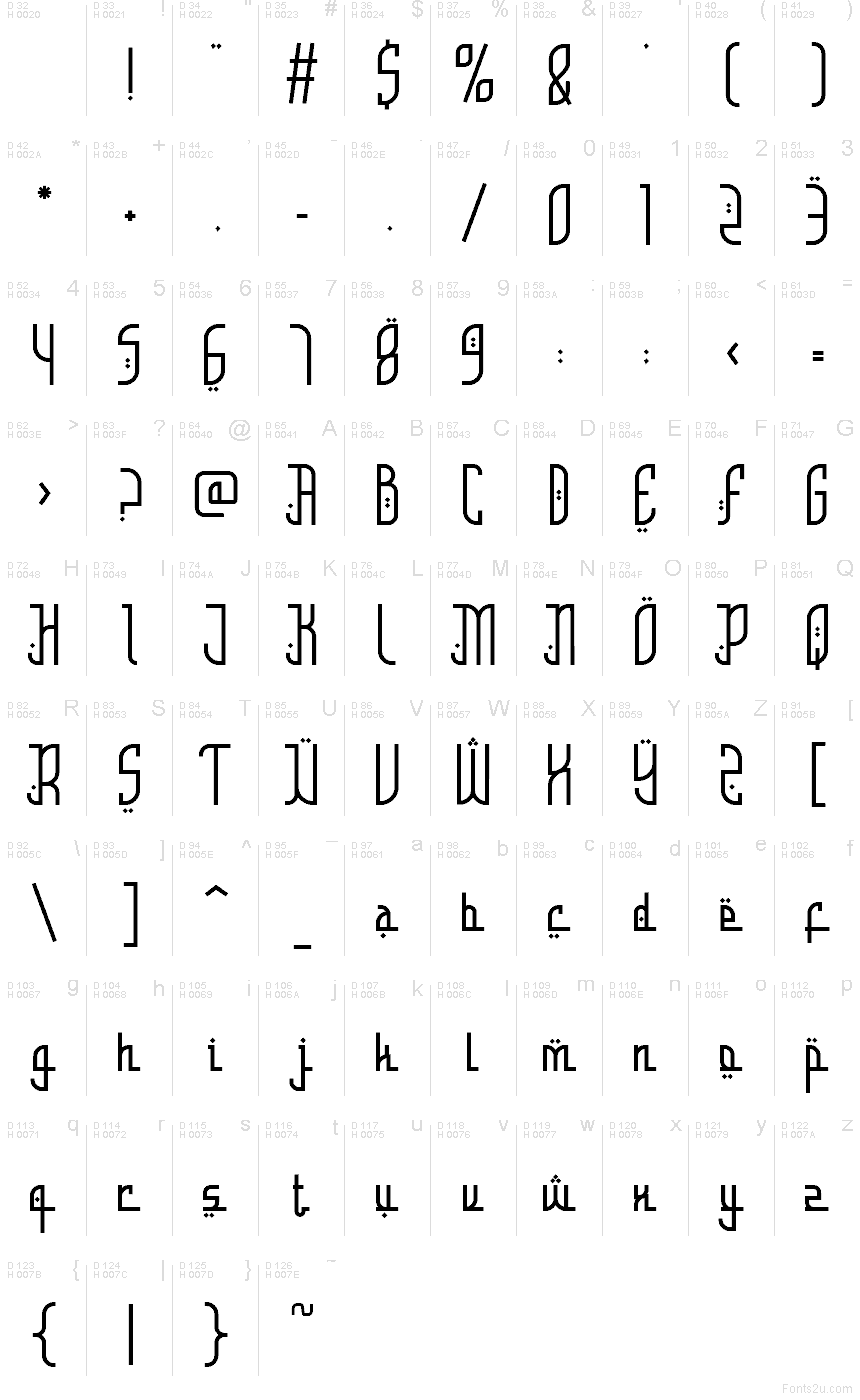
Nashir Nectar od Putracetol Studio je bezplatné písmo typu display inspirované arabským stylem, které se vyznačuje vysokými svislými tahy, plynulými spoji a diamantovými tečkami, jež odrážejí rytmus arabské kaligrafie. Design zaujme především svou siluetou: úzké svislé linie se tyčí nad širokým horizontálním pohybem, což písmu dodává ceremoniální, až ikonickou přítomnost, která přesahuje rámec běžného textu.
Tato struktura se skvěle hodí pro propagační akce k ramadánu, branding restaurací, plakáty kulturních akcí, obaly produktů a nadpisy na sociálních sítích, kde je žádoucí jasná reference na Blízký východ. Zvýšené dříky a tečkované akcenty navíc tvoří dekorativní rámec pro krátké nadpisy a loga, zejména v rozvrženích, která vyžadují stylizovaný vliv kaligrafie bez nutnosti přepínat na kompletní arabský text.